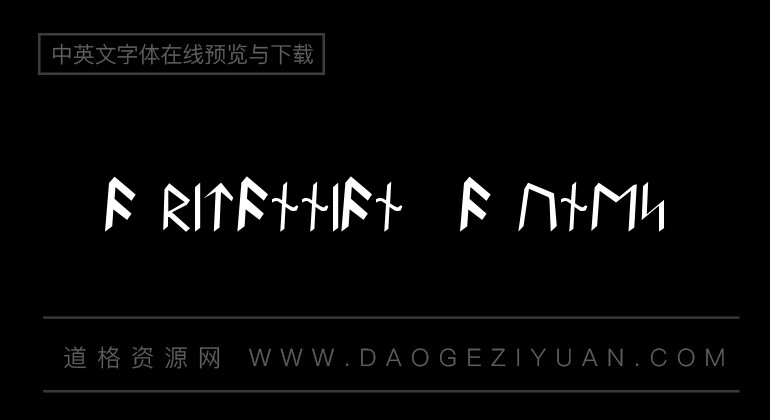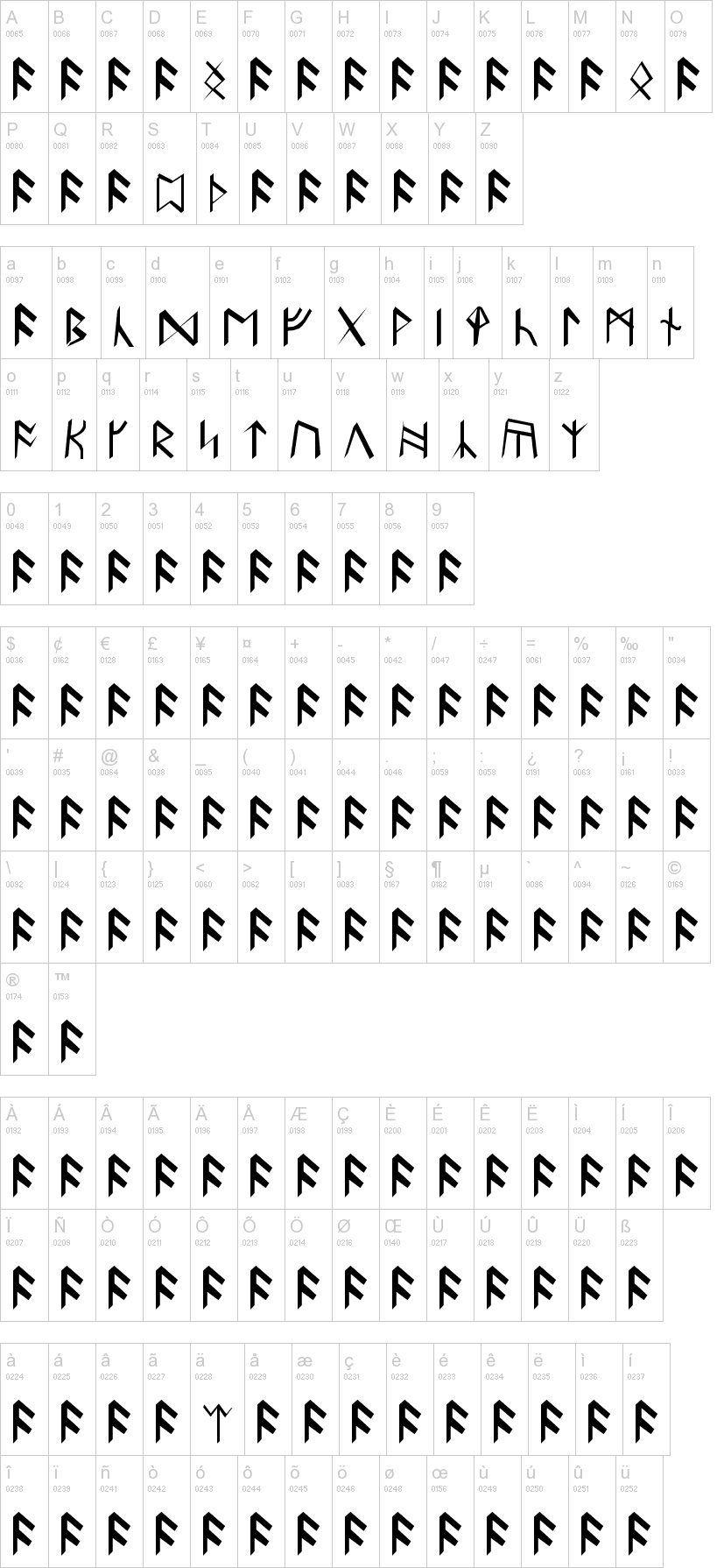
Britannian Runes
Britannian Runes 是一种基于古代北欧符号的字体,它源于日本动画《Code Geass》中的 Britannia 帝国,被用作该帝国的官方语言和文字。 这种字体的设计师是日本的 MARSNEV,他将古代符号重新设计成了一种新的字体,并推广到了动画迷和字体设计师之间。Britannian Runes字体看起来比较神秘和古老,它的线条粗细、斜度和笔画都很独特,让人联想到北欧神话中的符文。这种字体在设计海报、标志和书籍封面等方面非常流行,也被许多人用于纹身设计。 总之,Britannian Runes 是一种非常有趣、独特的字体,它的出现让人们对古代符号的重新认识,并且在视觉设计领域中具有广泛的应用前景。
Britannian Runes是一款非常不错的手写艺术字体,具有很好的视觉感,适合于文化类的宣传设计、商业类品牌的广告和产品包装设计以及个性化文字排版等较多场景。